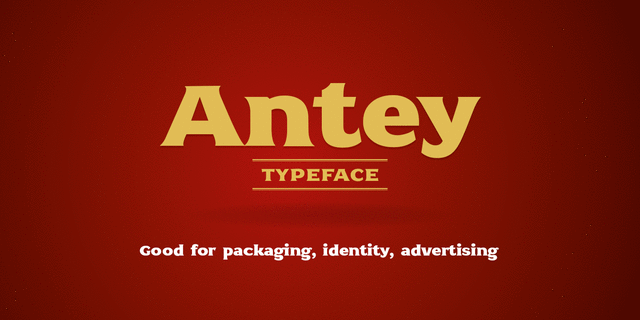
Antey – широкий и насыщенный шрифт с плавными засечками для дизайна дорогих и вкусных продуктов. Шрифт разработан Андреем Кудрявцевым в студии AKTF в 2012 году.